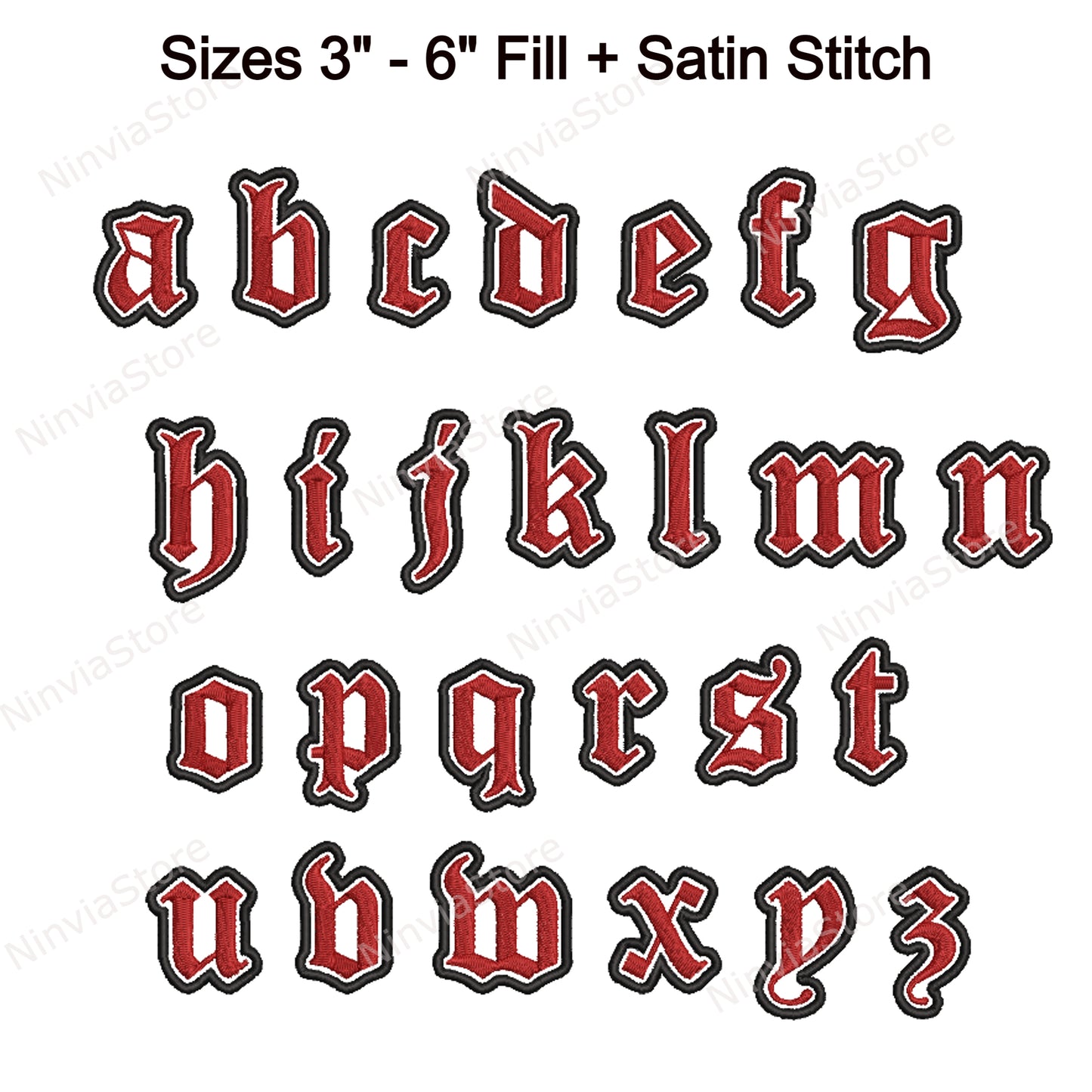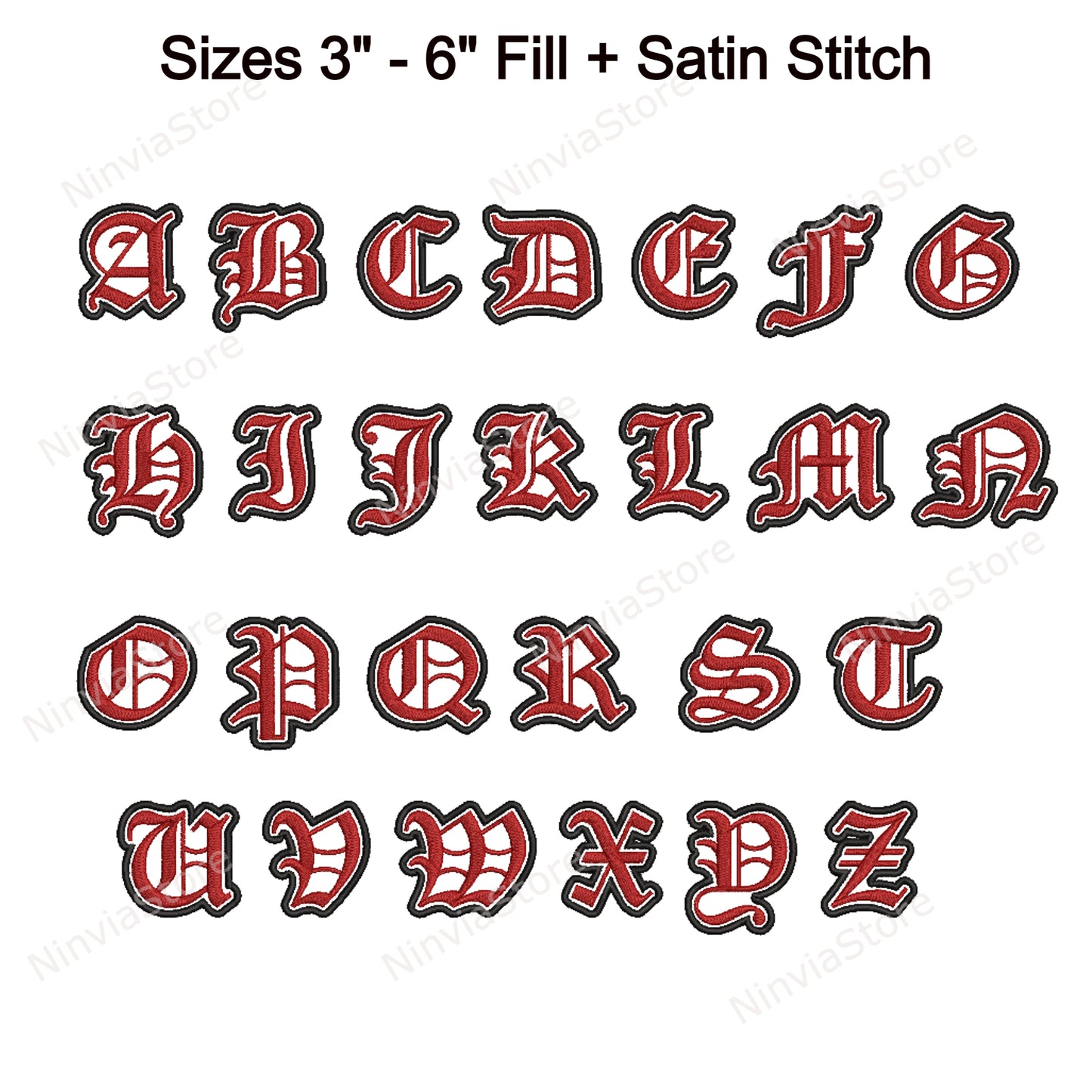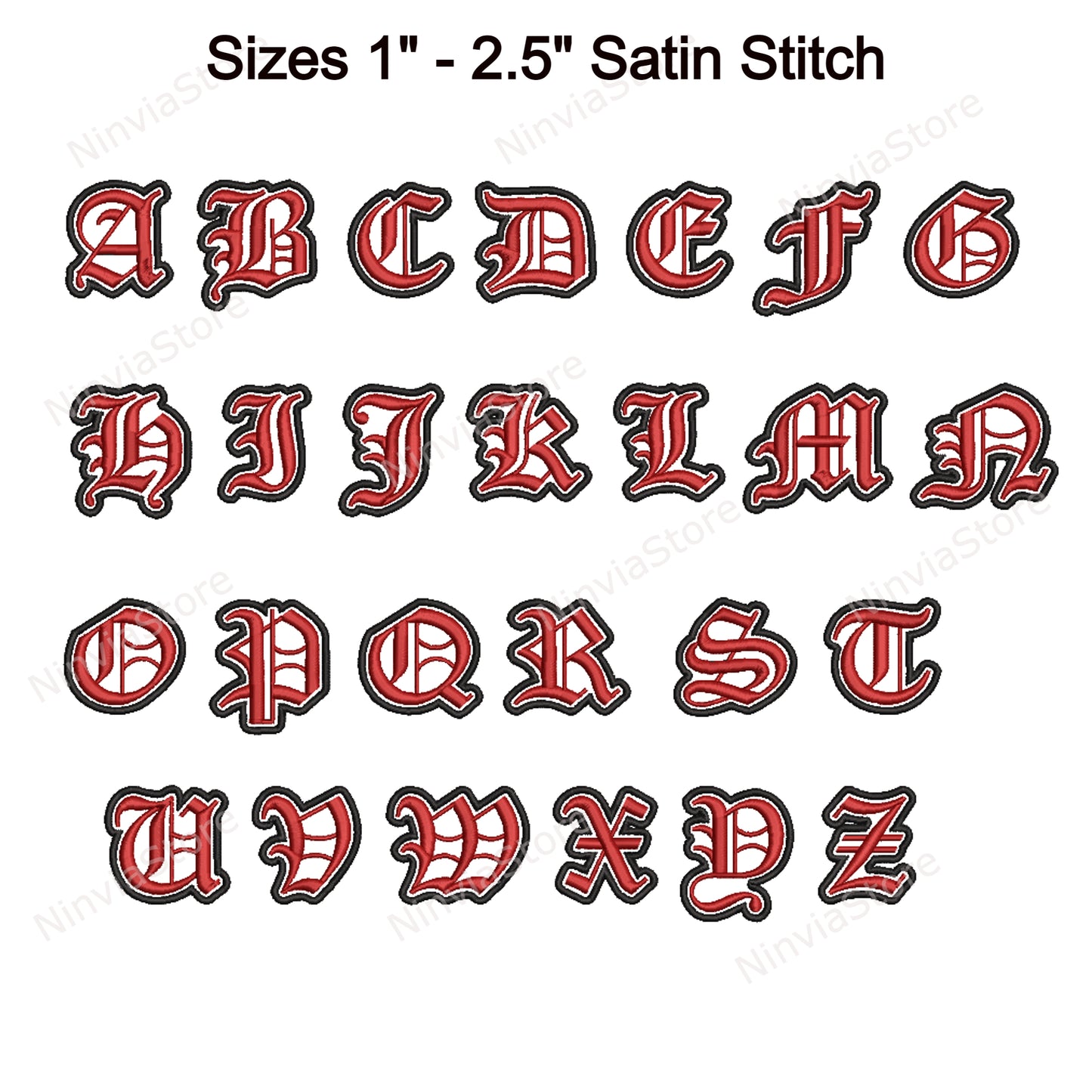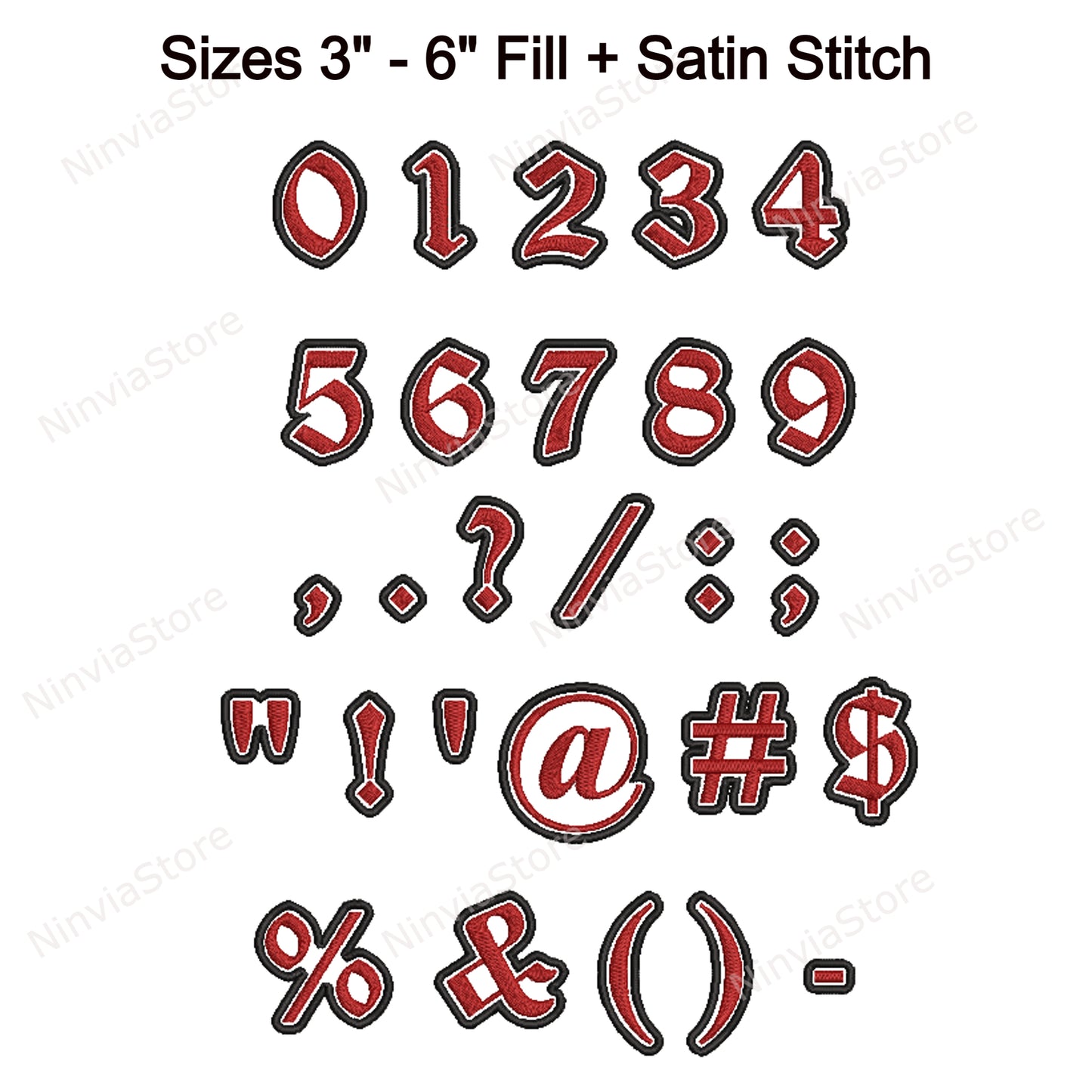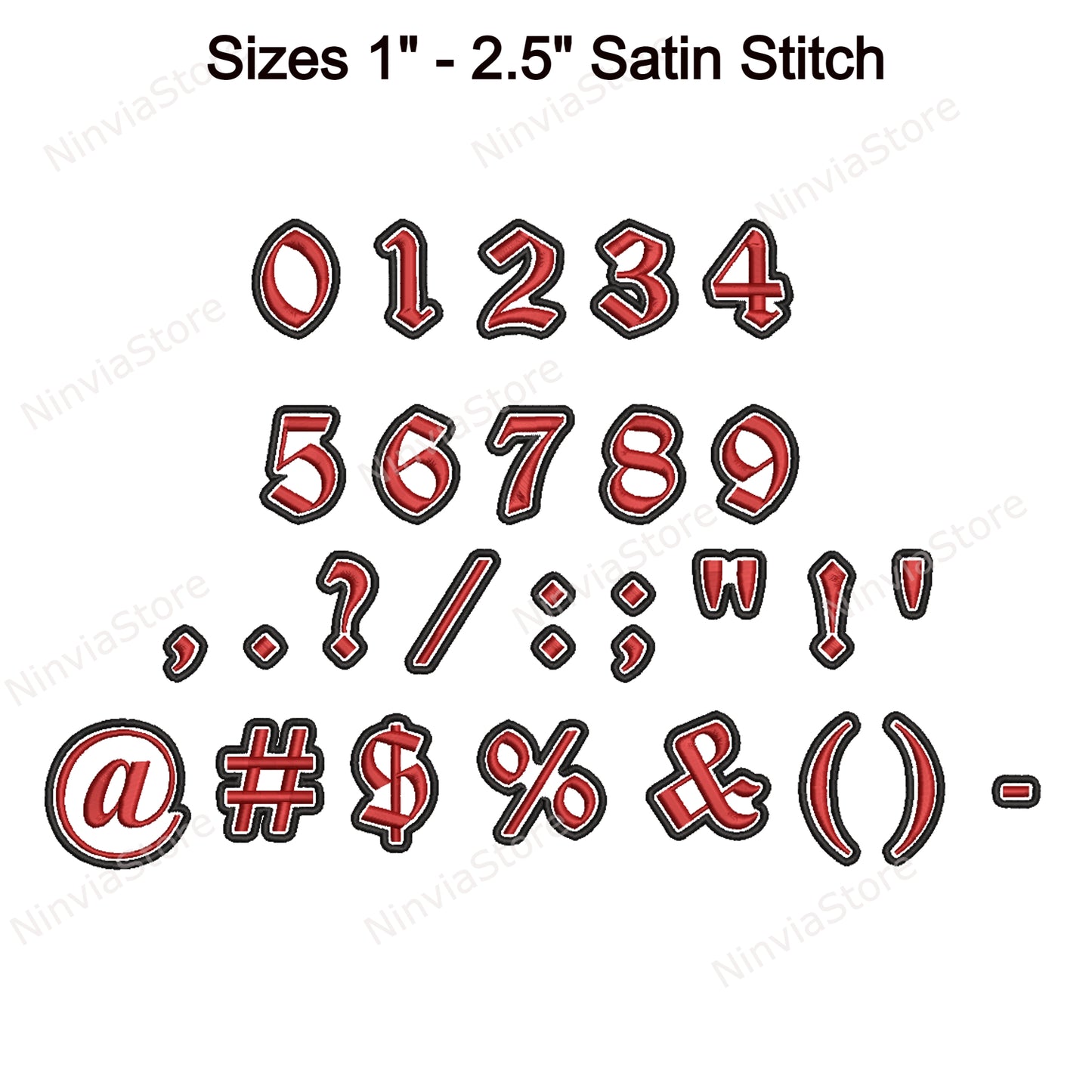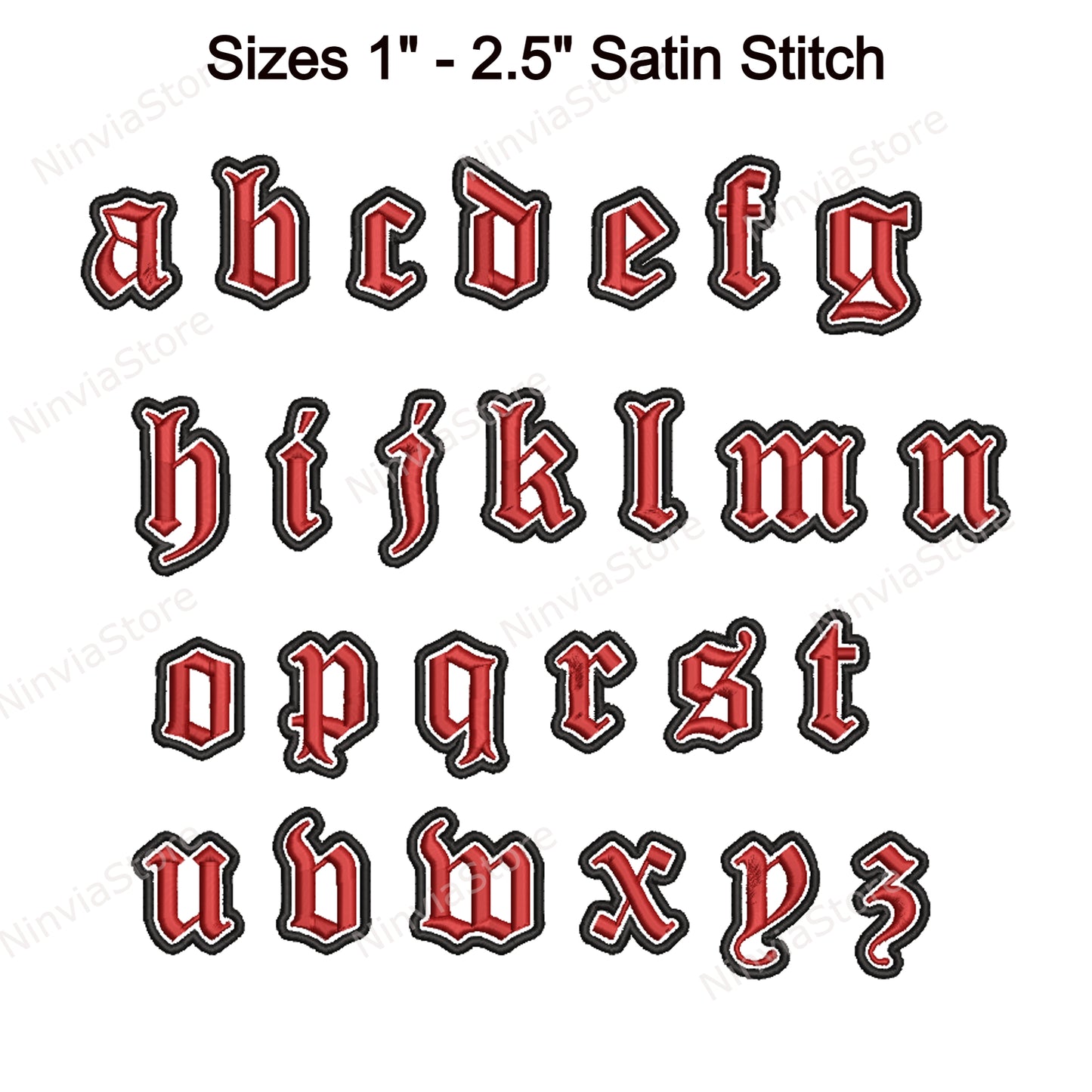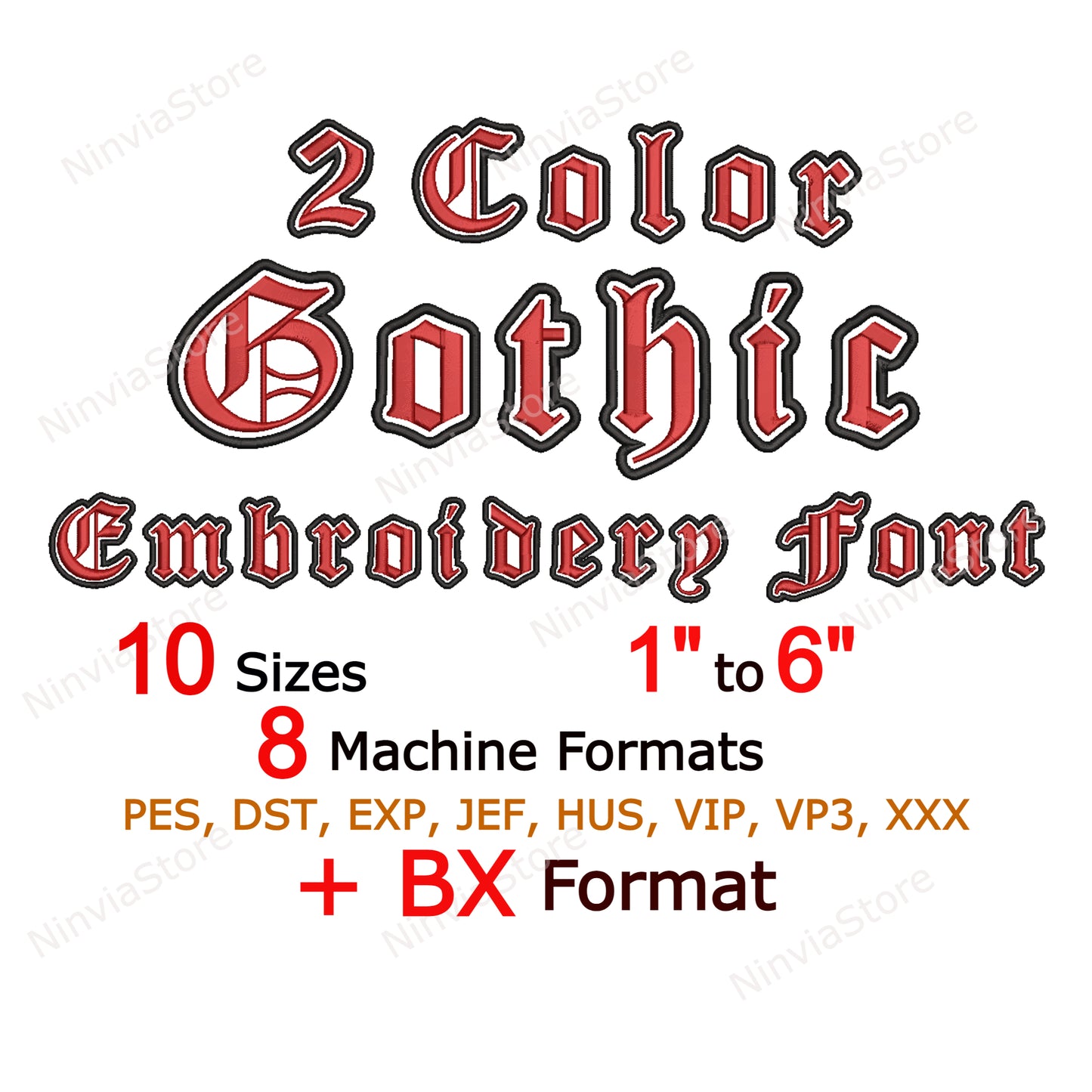
2-farbige Gothic-Maschinenstickschrift, 10 Größen, 8 Formate, alte englische BX-Schriftart, PE-Schriftart, Monogramm-Alphabet-Stickmotive
3 Zoll – Füllstich + Satinstich
4 Zoll – Füllstich + Satinstich
5 Zoll – Füllstich + Satinstich
6 Zoll – Füllstich + Satinstich
az(Kleinbuchstaben)